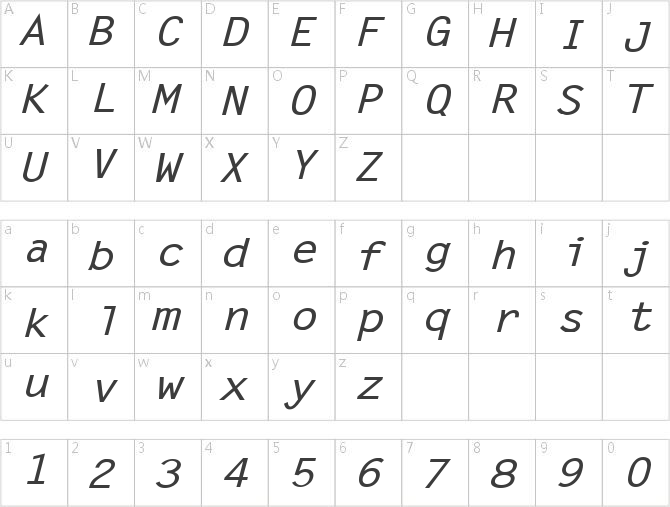
Lechter-Wide-Bold-Italic 詳情頁(yè)
Lechter-Wide-Bold-Italic字體字庫(kù)是一款讓人賞心悅目、百看不厭的英文字體,適合各類廣告和產(chǎn)品包裝設(shè)計(jì)應(yīng)用,字體大小0.05MB,格式為ttf字體,上傳用戶是快霸中國(guó),作者/版權(quán)方為未知